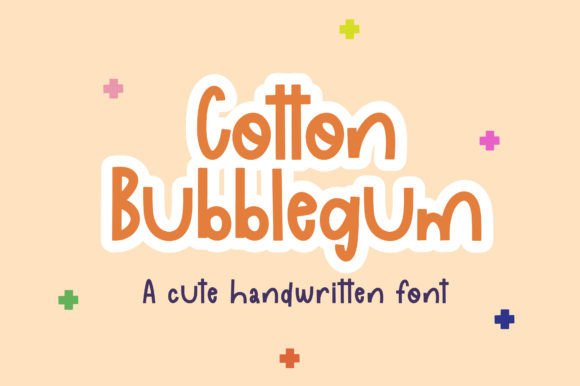
Cotton Bubblegum
Wenn Sie nach hochwertigen Assets wie Cotton Bubblegum suchen, ist dieses Premium-Paket eine fantastische Wahl für Ihre kreativen Projekte.
Egal, ob Sie POD-Produkte (Print on Demand), Hochzeitseinladungen oder Social-Media-Grafiken erstellen, Cotton Bubblegum ist die ideale Wahl.